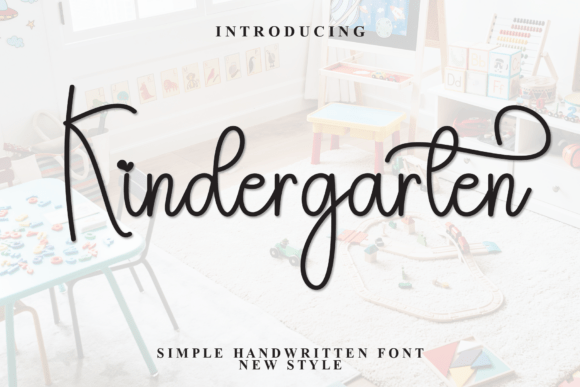
Kindergarten
์˜ฌ๋ฐ”๋ฅธ ๋””์ž์ธ ์š”์†Œ๋ฅผ ์ฐพ๋Š” ๊ฒƒ์€ ์–ด๋ ค์šธ ์ˆ˜ ์žˆ์ง€๋งŒ Kindergarten๋Š” ์ž‘์—…์„ ์ฆ‰์‹œ ํ–ฅ์ƒ์‹œํ‚ค๋Š” ๋›ฐ์–ด๋‚œ ์ปฌ๋ ‰์…˜์„ ์ œ๊ณตํ•ฉ๋‹ˆ๋‹ค.
์ •๋ฐ€ํ•˜๊ฒŒ ์ œ์ž‘๋œ Kindergarten๋Š” ๊น”๋”ํ•œ ๋ฒกํ„ฐ, ๋ถ€๋“œ๋Ÿฌ์šด ํƒ€์ดํฌ๊ทธ๋ž˜ํ”ผ ๋ฐ ์•ˆ์‹ฌํ•  ์ˆ˜ ์žˆ๋Š” ์ƒ์—…์šฉ ๋ผ์ด์„ ์Šค๋ฅผ ์ œ๊ณตํ•ฉ๋‹ˆ๋‹ค.
์ƒํ’ˆ์— ์ „๋ฌธ์ ์ธ ๊ฐ๊ฐ์„ ๋”ํ•˜๊ณ ์ž ํ•˜๋Š” ๊ณต์˜ˆ๊ฐ€, ๊ทธ๋ž˜ํ”ฝ ๋””์ž์ด๋„ˆ ๋ฐ ์†Œ๊ธฐ์—… ์†Œ์œ ์ž์—๊ฒŒ ์ ํ•ฉํ•ฉ๋‹ˆ๋‹ค.